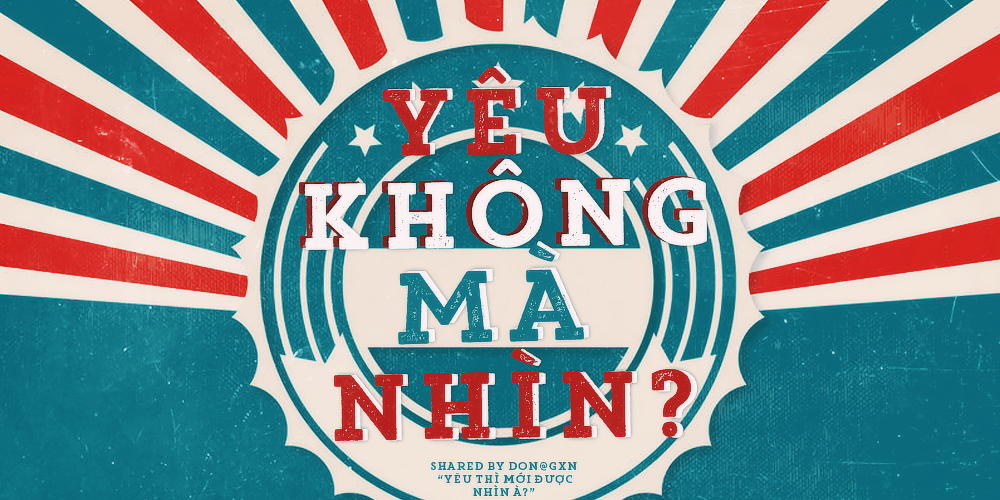
Tớ nghĩ font này đa số các bạn có hơi nhiều nhưng tớ chỉ share cho những bạn nào chưa có thôi :v Font này theo suy nghĩ bản thân, các bạn có thể để làm text phụ cho quotes/typo hoặc dùng làm retro style, quảng cáo, menu gì cũng được hết ( I think so =)))) )